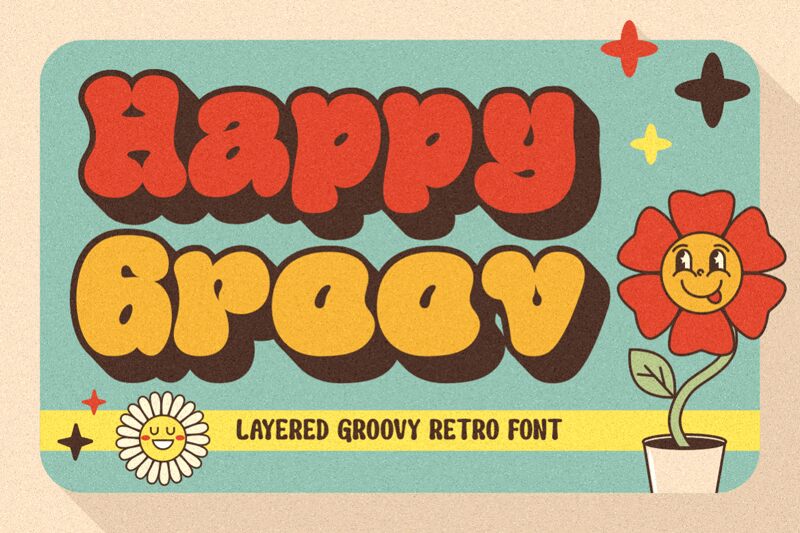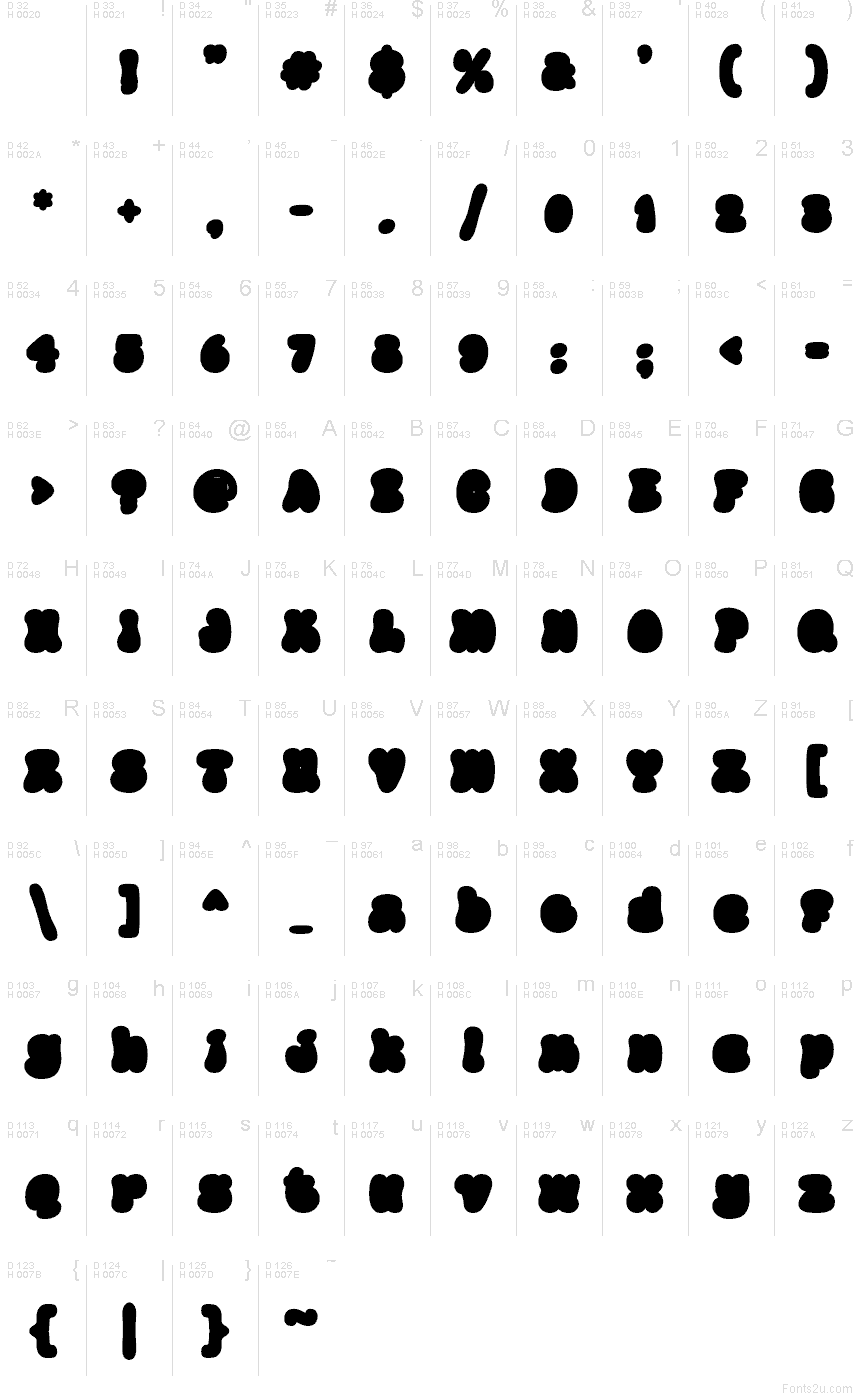
Happy Groov Two od Shanaf Studio to darmowy, kreskówkowy krój pisma w stylu lat 70. Litery są obłe i zaokrąglone, a ich bliskie zestawienie nadaje całości wesoły, niemal „rozlany” charakter, daleki od sztywnej geometrii.
To naturalny wybór do projektów skierowanych do dzieci, opakowań słodyczy i przekąsek, plakatów na imprezy, czy zabawnych tytułów na YouTube. Sprawdza się również na naklejkach, gadżetach i dużych napisach, gdzie te pękate sylwetki sprawiają wrażenie przyjaznych, zabawnych i nieco „kleistych”.